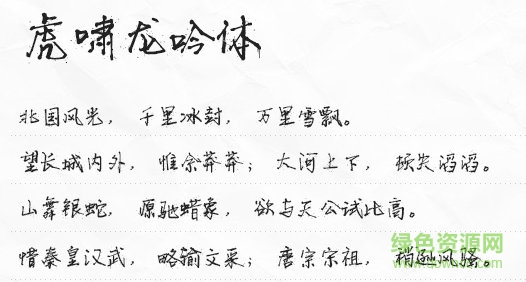
虎嘯龍吟體是原點(diǎn)創(chuàng)作的一款手寫字體,字跡獨(dú)特鮮明,非常具有個(gè)性魅力,而文字周圍匯聚了一層斑點(diǎn),讓字體在若隱若現(xiàn)間更有質(zhì)感,綠色資源網(wǎng)誠意推薦!
墨色橫飛,筆鋒縱橫,盡顯龍吟虎嘯之勢(shì)!
虎嘯龍吟體字跡是一款非常杰出的硬筆書法字體,獨(dú)有的斑點(diǎn)設(shè)計(jì)并未讓文字顯得凌亂,而是增添了一絲煙霧飄渺的感覺,可以使用在廣告策劃、海報(bào)設(shè)計(jì)、藝術(shù)創(chuàng)作等行業(yè)。